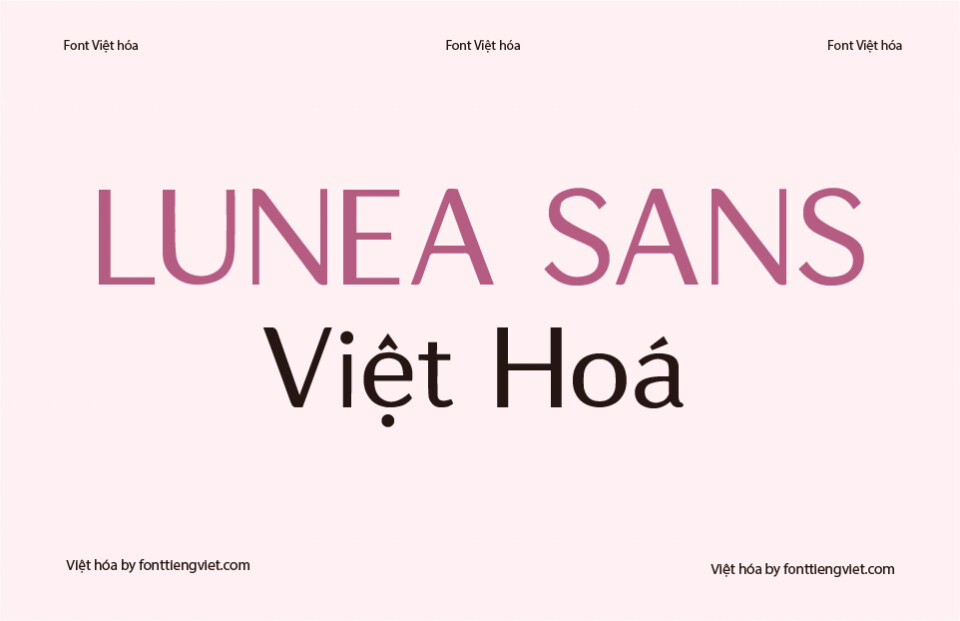
Font Việt hóa 1FTV VIP Lunea Sans
Giới thiệu về Font Việt hóa 1FTV VIP Lunea Sans
Trong thế giới đồ họa hiện nay việc lựa chọn một bộ Font Miễn Phí phù hợp đóng vai trò then chốt giúp truyền tải thông điệp hiệu quả. Font Việt hóa 1FTV VIP Lunea Sans nổi lên như một lựa chọn hàng đầu cho các nhà thiết kế tìm kiếm sự tinh tế và chuyên nghiệp. Đây là một bộ phông chữ thuộc họ không chân (Sans Serif) mang phong cách tối giản nhưng không kém phần sang trọng. Với đường nét thanh mảnh và cấu trúc hình học chuẩn xác bộ font này giúp mọi văn bản trở nên dễ đọc và bắt mắt hơn bao giờ hết. Đặc biệt phiên bản đã được 1FTV Việt hóa hoàn chỉnh giúp người dùng Việt Nam sử dụng các ký tự có dấu một cách mượt mà không lo lỗi font.
Đặc điểm nổi bật của bộ Font Việt hóa 1FTV VIP Lunea Sans
Sự kết hợp hoàn hảo giữa hiện đại và cổ điển
Font Việt hóa 1FTV VIP Lunea Sans sở hữu một vẻ đẹp giao thoa độc đáo. Các chữ cái được bo góc nhẹ nhàng tạo cảm giác thân thiện nhưng vẫn giữ được sự nghiêm túc cần thiết của một phông chữ hiện đại. Điều này khiến nó trở nên cực kỳ linh hoạt trong nhiều bối cảnh khác nhau từ trang trí thiệp mời cho đến thiết kế giao diện ứng dụng di động. Khả năng hiển thị sắc nét trên cả màn hình kỹ thuật số lẫn bản in là một ưu điểm lớn giúp Lunea Sans ghi điểm trong mắt cộng đồng sáng tạo.
Hỗ trợ tiếng Việt trọn bộ và tối ưu hiển thị
Vấn đề lớn nhất khi sử dụng các font chữ quốc tế là thiếu các ký tự dấu tiếng Việt hoặc dấu bị lệch so với thân chữ. Tuy nhiên với Font Việt hóa 1FTV VIP Lunea Sans mọi rào cản này đã được xóa bỏ. Đội ngũ kỹ thuật đã tinh chỉnh tỉ mỉ từng dấu sắc dấu huyền và các ký tự đặc biệt như đ ê ô để đảm bảo sự cân đối về mặt thị giác. Khoảng cách giữa các chữ cái (kerning) cũng được tối ưu hóa giúp văn bản dài không gây mỏi mắt cho người xem.
Ứng dụng thực tế của Font Việt hóa 1FTV VIP Lunea Sans
Sử dụng trong thiết kế bộ nhận diện thương hiệu
Nhờ vẻ ngoài chuyên nghiệp Font Việt hóa 1FTV VIP Lunea Sans thường xuyên được lựa chọn để làm logo hoặc font chữ chủ đạo cho các bộ nhận diện thương hiệu cao cấp. Nếu bạn đang làm việc trong lĩnh vực thời trang mỹ phẩm hoặc công nghệ bộ font này sẽ mang lại cảm giác đẳng cấp và hiện đại ngay lập tức. Tính đơn giản của nó giúp thương hiệu dễ dàng in ấn trên nhiều chất liệu khác nhau mà vẫn giữ nguyên được bản sắc vốn có.
Trình bày văn bản và ấn phẩm truyền thông
Bên cạnh việc làm tiêu đề Lunea Sans còn hoạt động rất tốt ở định dạng văn bản nội dung. Với nhiều biến thể độ dày khác nhau từ mảnh (Light) đến đậm (Bold) bạn có thể dễ dàng phân cấp thông tin trong các poster infographic hay bìa sách. Việc kết hợp các kiểu chữ khác nhau trong cùng bộ Font Việt hóa 1FTV VIP Lunea Sans giúp thiết kế của bạn có sự đồng nhất và chuyên nghiệp mà không cần sử dụng quá nhiều loại phông chữ khác nhau gây rối mắt.